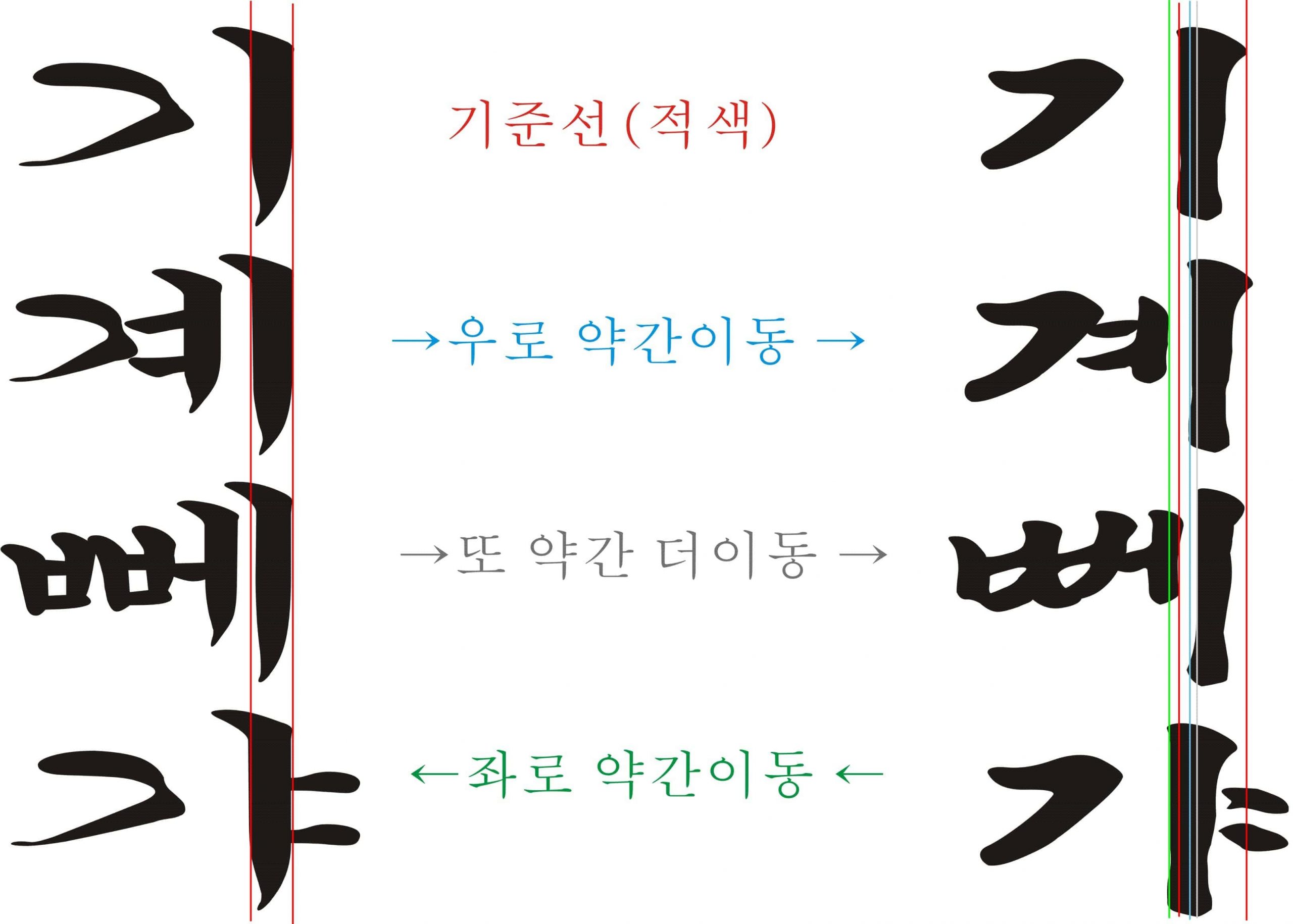
제승당 유허비
경남 통영시 한산도 제승당에는 朴正熙 대통령이 가장 존경했던 인물 충무공 이순신 장군을 기리는 제승당유허비(制勝堂遺墟碑)가 있는데 한글로 번역되어 있다.
한글 번역 비석을 박정희 세로글_V체로 옮겨본다.
《박정희서체》새로글 정렬
이번 시간에는 서체를 제작할 때, 세로글 정렬 또는 세로글 맞춤에 관하여 설명하고자 한다.
보신바와 같이 한글 세로글은 가로글에서 느낄 수 없는 중후감과 빼어난 매력이 넘쳐난다. 한글 세로글도 이렇게 멋진 글인데 요즘 거의 사용하지 않는 것이 안타깝다. 하지만 한글을 사랑하는 의미에서 유행의 변화는 늘 싸이클을 타듯 복고풍이 불어 세로글이 다시 환영 받을 날이 오리라고 기대하고 이 글을 읽기를 바란다. 혹시 서체 제작에 관심 없으신 분이라면 이 페이지를 벗어나는 것이 정신 건강에 좋겠다. 딱딱한 강의(?)이니까.
[tip]세로글에서 가장 중요한 것은 ‘세로 기준선‘이다.[/tip]
기준선을 그어 놓고 튀어나온 글자나 쏙 들어간 글자를 선에 맞춰 정렬시켜주면 세로글이 완성되는 간단한 방법이다.
박정희세로글_V체도 박정희국력체_M 을 불러와서 세로 기준선에 맞춰 정렬한 서체라고 생각하면 된다. 그래서 V체는 세로글, M체는 가로글로 2개의 서체가 만들어졌다.
그런데 여기서 좀 더 세분해 보면, 획수가 늘어나는 모음이나 쌍받침이 나타날 때는 약간의 (+)이동이 필요하고, 가 갸처럼 점이 튀어나오는 획수의 정렬은 약간 (-)변화를 줄 필요가 있다. 여러 방법을 시도해 보다가 내가 정한 세로 기준선 원칙을 다음과 같이 정의하였다.
그림으로 설명하면 이해가 더 빠를 것이다.
3번, 4번은 내가 제작한 서체이고 그외 전부 서체회사에서 개발한 글꼴인데 세로쓰기 해 본 것이다. 정렬이 잘 된 것도 있고 들어갔다 나왔다 요철이 심한 글자도 눈에 띈다. 모두 가로 글쓰기에만 염두에 두고 개발했기 때문이라 생각되므로 참고하기 바란다.
빨간 기준선에 맞춰 정렬한 1번과 2번은 가장 쉬운 방법으로 세로글 정렬하는 방법이다. 이제부터 2번 궁서체에 미세한 이동 변화를 주어서 좀 더 정렬된 세로글을 만들까 한다.
[important]기준선은 한글 ‘기‘ 자로 잡는다. ‘기’에서 모음 획수가 늘어나는 ‘게,계,갱,괙’은 기준선에서 약간 우측으로 (+)이동시키고, 획수가 더 늘어나는 ‘께,뻬,꽥,쒜’는 이 보다도 또 약간 더 우측으로 이동시켜 준다. 반대로 ‘가, 갸’는 점의 무게를 감안해서 기준선에서 약간 왼쪽으로 이동시킨다[/important] 특히 주의할 점은 경험상, 이동시킬 때 미세한 차이를 두고 이동시켜야 완성도가 높았다. 이동 폭이 너무 크면 오히려 요철이 심하다. 위의 9번의 경우가 그렇다.
이 공식은 참고만 하고 전체적으로 문장을 만들어가면서 한 자 한 자 세로글을 수정 정리해 나가면서 자신만의 멋진 세로글을 만들어 보는 것이 좋겠다.
박대통령 生家 입구에 유독 눈에 띄는 기념비가 있었다. 대통령께서 직접 지은 글이라고 적혀있다.
[help]가로글을 내가 만든 세로글 폰트로 바꾸어 보았다[/help]
어떻습니까?
朴正熙 대통령 글씨다운가요? 평가는 여러분께서 하시기 바랍니다.